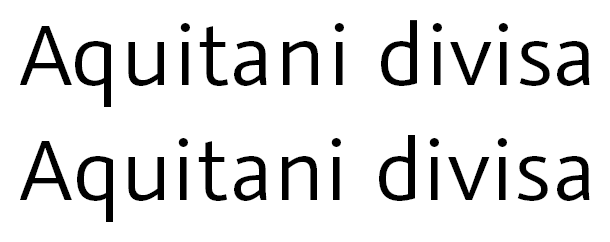
Skolar - Welche Sans Serif (mit Versaleszett)?
ich suche eine zur Skolar passende Sans Serif (am besten mit Versaleszett). Der Zeichensatz muss zwar nicht so überwältigend wie der der Skolar ausgebaut sein, aber so ein paar typografische Besonderheiten wie diskrete Ligaturen, das lange historische s und die Möglichkeit proportionale Ziffern einzuschalten wären schon schön.
Die Graublau gefällt mir schon sehr, aber auch die Rooney Sans hat es mir angetan. Danke.
Der Thread ist zwar ein Jahr alt, aber ein paar Worte zur Graublau Sans:
Jedes Mal, wenn ich sie sehe, denke ich: Sie könnte so schön sein, wenn Metrics und Kerning besser wären. Beides ist sehr unregelmäßig. Es gibt so wenige serifenlose Schriften, die schön und zugleich hoch lesbar sind. Dann trifft man mal eine, die in Bezug auf die Zeichenformen ein großes Meisterwerk ist. Und dann versagt sie bei den Seitenabständen der Zeichen total. Das ist richtig bitter. Ich kann mir das nur so erklären, dass Georg Seifert die Arbeit an Metrics und Kerning langweilig findet. Dass er kein Gefühl für Leerräume hat, lässt sich angesichts der Qualität und Harmonie der Zeichenformen ausschließen.
Die Abstände zwischen geraden Außenstämmen sind überproportional groß.
Beispiele: Aquitani divisa. Angesichts der großen Abstände zwischen q, u und i müsste das Paar Aq nicht negativ, sondern positiv gekerned sein, u. z. mindestens +10 Einheiten. Ähnliches gilt für die Kombination ivi. Da sind die Abstände zu gering. Das d wirkt abgehängt.
Tatsächlich ist das optische Kerning in Indesign besser als das font-interne Kerning, und das will schon was heißen. Plain Metrics und Kerning der FF Kievit sind wesentlich besser. Und das schmerzt mich wirklich sehr, weil die Graublau Sans so wunderbar leichtfüßig ist. Die Kievit wirkt dagegen fast schon plumb und statisch. Ich würde aus dem Schwärmen nicht mehr raus kommen, aber die Abstände der Zeichen der Graublau Sans sind eine Katastrophe. Und das kann unmöglich daran liegen, dass Georg Seifert kein Gefühl für Abstände hat, denn schließlich hat er die Abstände innerhalb der Zeichen  sehr sorgsam gewählt. Im Vergleich zur Gestaltung der Zeichen ist Kerning aber eine wenig spannende Arbeit, die gleichzeitig viel Konzentration erfordert. Eine andere Erklärung habe ich nicht dafür, dass die Graublau Sans in Bezug auf die Seitenabstände unfertig geblieben ist.
Edit: Ich vermute, dass das Kerning ganz oder teilweise von einer Automatik erledigt worden ist.
Wer das optische Kerning in Indesign mit dem Original-Kerning vergleichen will, sollte übrigens keinen großen Schriftgrad wählen, weil sich das optische Kerning mit dem Schriftgrad verändert. Also für einen Vergleich lieber 12 pt aufzoomen.
Edit 2:
Theoretisch ist es möglich, das optische Kerning von Indesign aus einem mit Indesign erstellten PDF auszulesen und in Fonts zu übertragen. Unter Umständen müssen die Plain Metrics von den im PDF gespeicherten Abständen subtrahiert werden. Das geht gut mit Excel o. ä. Aber Kerning-Automatiken können meiner Meinung nach nicht das menschliche Auge ersetzen.
Ansonsten gibt es da noch den ikern-Service von Igino Marini und den DTL Kernmaster.
Die wichtigste Frage wäre dabei, welche Version du überhaupt benutzt. Die Schrift erschien ursprünglich 2008 und wurde seitdem von Georg fortlaufend weiterentwickelt. Aktuell ist der 2.0-Release, der in jeder Hinsicht (Zeichenformen, Metrik, Kerning) überarbeitet ist.
Öffentliche Mutmaßungen von wegen »hat er wohl keine Lust gehabt« und »wurde wohl automatisch gemacht« sind etwas ärgerlich. Sie stimmen natürlich nicht, aber sind solche Gerüchte einmal in die Öffentlichkeit gesetzt, wird man sie schwer wieder los.
Ich kann mit der von dir genannten Testphrase und der aktuellen Version keine Probleme feststellen und auch nicht bestätigen, dass das optische Kerning von InDesign besser wäre. Bedenke, dass Kerning keine Wissenschaft ist und in der Regel schon zwei unterschiedliche Designer das gleiche Wort unterschiedlich kernen würden. Kommt halt immer darauf an, wie man den Weißraum einschätzt, der sich bei den meisten Buchstabenkombination nicht mathematisch genau beschreiben lässt.
Ich rede vom 2.0-Release (die bei Myfonts derzeit gelistete Version). Und ich kann dir in Bezug auf das subjektive Empfinden von Weißräumen zwar bedingt zustimmen, aber im Fall der Graublau Sans steht der Umgang mit den Weißräumen innerhalb der Zeichen in totalem Kontrast zum Umgang mit den Weißräumen zwischen den Zeichen.
Oben original Metrics und Kerning.
Unten Indesign optisches Kerning + 6.
Hast Du das mit Georg schon mal privat geklärt? Wenn nein, finde ich diese öffentliche Anprangerung -- so berechtigt sie sein mag -- unans-tändig.
Vielleicht noch etwas Positives: irgendwann gab es mal (glaube auch von mir) Kritik wegen einer fehlenden g-Alternative. Schön zu sehen, dass diese inzwischen mit zum Repertoire gehört (und für mich ein kleines Zeichen, dass offensichtlich keine Beratungsresistenz vorliegt).
Kievit und Co. bekommen wohl langsam Konkurrenz. ;-)
Die Kommentar-Funktion scheint auf der Seite defekt zu sein. Und eine simple Sterne-Bewertung  würde vermutlich auf die Qualität der Schrift und nicht auf die Qualität des Fonts bezogen werden. Für die Schrift würde ich fünf Sterne vergeben. Für den Font derzeit drei.